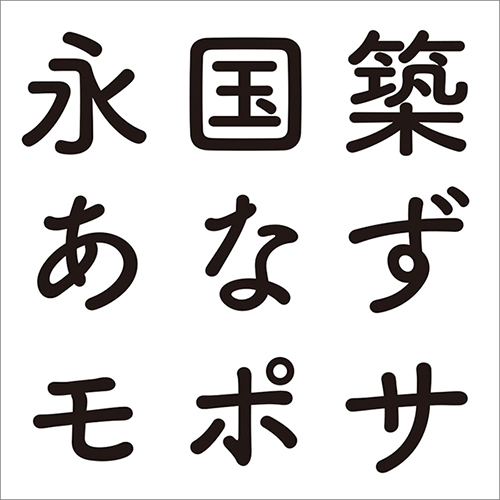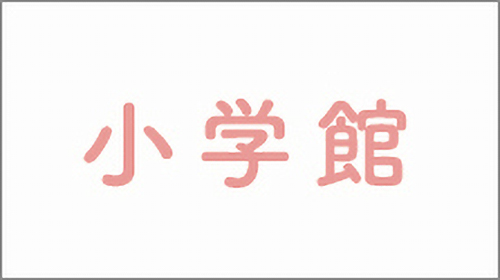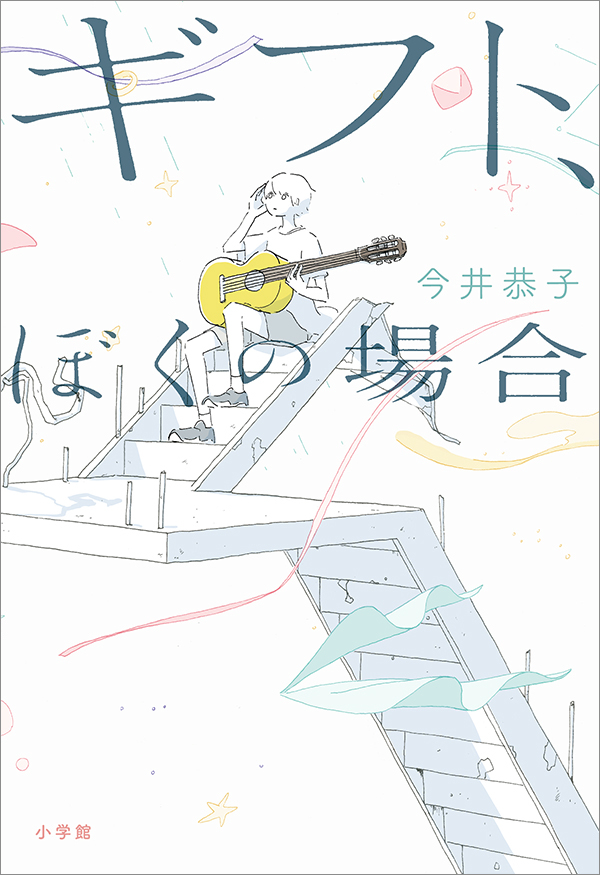
今回は書籍『ギフト、ぼくの場合/今井恭子』の使用フォントをご紹介。本記事はデザイン構成において重要な「フォント」の選定プロセスや加工方法を、貴重なプロの実例から紐解いてデザイン制作に役立てる連載です。
流れるような筆致の文字でシリアスかつ明るい印象に
両親の離婚を機にギターに触れるのをやめてしまった少年が、バンドの子の代役で再びギターを弾くことになり、その練習を通して将来の夢を見つける姿を描いた物語。『こんぴら狗』で第67回小学館児童出版文化賞を受賞した今井恭子の新作で、「死」や「貧困」などの重いテーマをも扱いつつ、「希望」を感じさせる内容になっている。
表紙カバーでは、そのシリアスでありながら夢や希望を感じさせる内容が、流れるような筆致の繊細なタイトル文字や、主人公の心の葛藤をイメージした内省的なイラスト、パステル調の配色などで表現されている。
Font.01「秀英明朝 L」「築地体三号細仮名」
流麗な明朝体に平体をかけシリアスかつ優しい印象に
メインタイトルのうちカタカナと漢字は歴史ある秀英舎の活字書体の特徴を受け継いだ端正な明朝体「秀英明朝 L」(モリサワ)、ひらがなは東京築地活版製造所の三号活字をもとに覆刻されたかな書体「築地体三号細仮名」(SCREENグラフィックソリューションズ)がベースに。
作品のシリアスな雰囲気や主人公の少年の心象風景を表現するため、平体をかけたり太さや濁点を調整したり、エッジにラフな加工を施すなどの工夫がされている。また、異なる2書体で文字組みしたときに違和感が出ないような調整も行われた。
Font.02「筑紫B丸ゴシック L」
パステルトーンに合わせ優しく柔らかい書体に
著者名部分は、温かみのある丸みを帯びたフォルムの丸ゴシック体「筑紫B丸ゴシック L」(フォントワークス)に。背景のパステル調のモチーフに合わせて優しく柔らかい書体が選択された。
Font.03「筑紫B丸ゴシック B」
温かみのある味わい深い丸ゴシック体をチョイス
出版社名「小学館」部分は、著者名と同様に温かみのある味わい深い丸ゴシック体「筑紫B丸ゴシック」(フォントワークス)がチョイスされた。全体のバランスや可読性なども意識し、ウェイトは「B」が選択されている。